Bí quyết chọn font chữ hiệu quả – không chỉ là chữ, đó là cảm xúc!
Bạn có bao giờ tự hỏi tại sao cùng một nội dung, nhưng khi đặt vào thiết kế này lại trông sang trọng, chuyên nghiệp, trong khi ở thiết kế khác lại có vẻ lộn xộn và kém thu hút? Bí mật thường nằm ở một chi tiết nhỏ nhưng mang sức mạnh to lớn: Cách bạn chọn và sử dụng Font chữ.
Trong đồ họa, phông chữ không chỉ là những chữ cái vô tri vô giác ghép lại với nhau. Chúng là công cụ trực quan mạnh mẽ giúp truyền tải cảm xúc và định hình cấu trúc thông tin cho người xem.
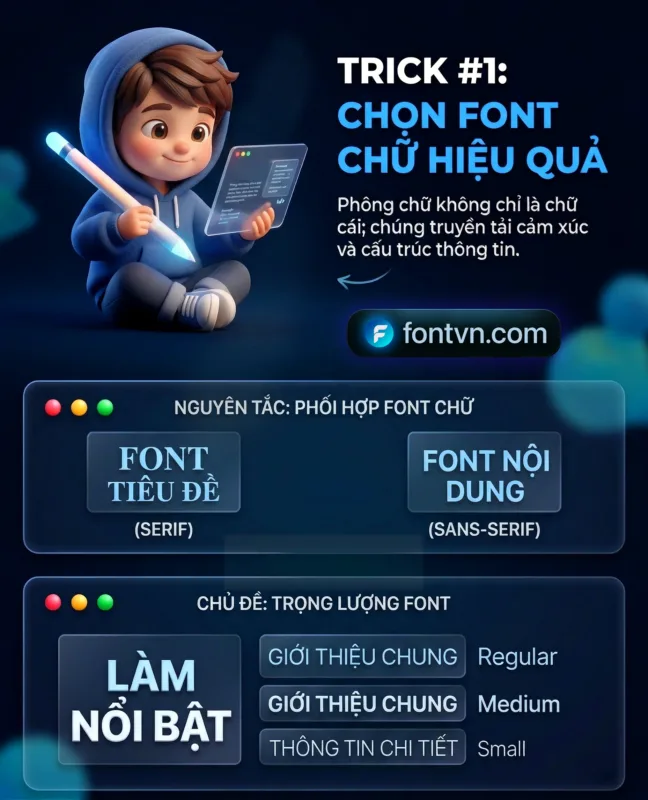
Hôm nay, hãy cùng khám phá 2 nguyên tắc cốt lõi để làm chủ font chữ trong thiết kế nhé!
1. Nguyên Tắc Phối Hợp Font Chữ: Sự Cân Bằng Hoàn Hảo
Một sai lầm phổ biến của người mới bắt đầu là sử dụng quá nhiều font chữ khác nhau, hoặc chọn những font “đánh nhau” chan chát. Cách an toàn và hiệu quả nhất là kết hợp một font có chân (Serif) và một font không chân (Sans-Serif).
Sự tương phản giữa hai loại font này tạo ra sự phân cấp rõ ràng, giúp mắt người xem dễ dàng phân biệt đâu là điểm nhấn, đâu là thông tin diễn giải.
| Đặc Điểm | Font Tiêu Đề (Serif – Có chân) | Font Nội Dung (Sans-Serif – Không chân) |
| Cấu trúc | Có các nét gạch nhỏ ở đầu và cuối nét chữ | Cấu trúc nét trơn, gọn gàng, không có nét gạch thừa |
| Cảm giác mang lại | Cổ điển, thanh lịch, trang trọng, đáng tin cậy | Hiện đại, trẻ trung, thân thiện, tối giản |
| Cách ứng dụng | Tuyệt vời để làm Tiêu đề lớn, logo, câu quote nhấn mạnh | Hoàn hảo cho Đoạn văn bản dài, thông tin chi tiết, giao diện UI |
2. Sử Dụng Trọng Lượng (Font Weight) Để Tạo Điểm Nhấn
Đôi khi, bạn không cần đến 2 hay 3 font chữ khác nhau để tạo sự phân cấp. Chỉ cần sử dụng duy nhất một bộ font (Typeface) nhưng thay đổi độ dày mỏng (Weight) của nó là đủ để dẫn dắt ánh nhìn của độc giả.
Việc thay đổi trọng lượng giúp nhóm các thông tin liên quan lại với nhau và chỉ ra cho người xem biết họ nên đọc cái gì trước, cái gì sau.
| Trọng lượng Font (Weight) | Vai trò trong thiết kế | Ứng dụng thực tế |
| Dày (Bold / Black) | LÀM NỔI BẬT – Bắt lấy sự chú ý ngay lập tức | Dành cho Tiêu đề chính, Từ khóa quan trọng, Nút bấm (Button) |
| Vừa (Medium) | DẪN DẮT – Nhấn mạnh ở mức độ vừa phải | Dành cho Tiêu đề phụ, Đoạn mở đầu (Giới thiệu chung) |
| Mỏng (Regular / Light) | DIỄN GIẢI – Tạo sự thoải mái khi đọc lâu | Dành cho các đoạn văn bản dài, Thông tin chi tiết, Chú thích nhỏ |
Tóm lại
Typography (Nghệ thuật chữ) là một thế giới rộng lớn, nhưng chỉ cần nắm vững cách phối hợp Serif & Sans-Serif cùng thủ thuật điều chỉnh Trọng lượng (Weight), bạn đã nắm trong tay chìa khóa để làm cho mọi ấn phẩm thiết kế trở nên gọn gàng, chuyên nghiệp và có “hồn” hơn rất nhiều.